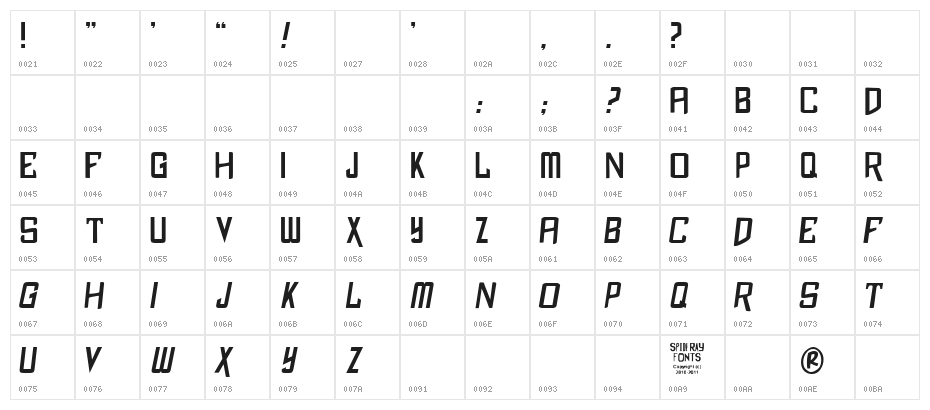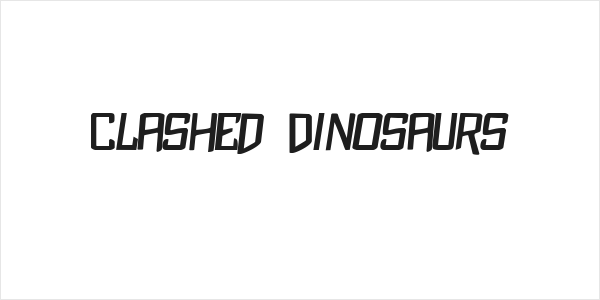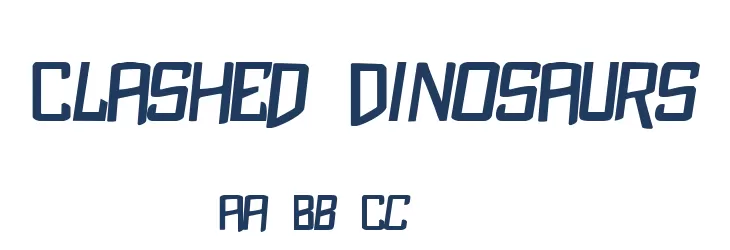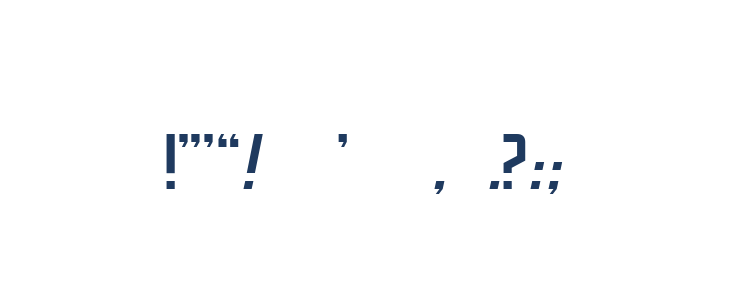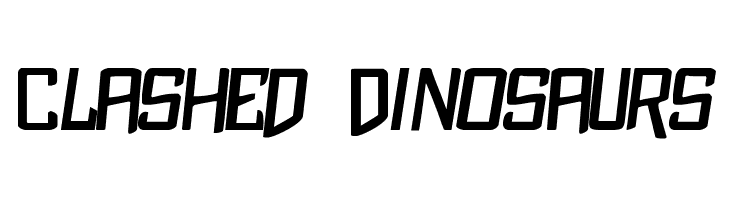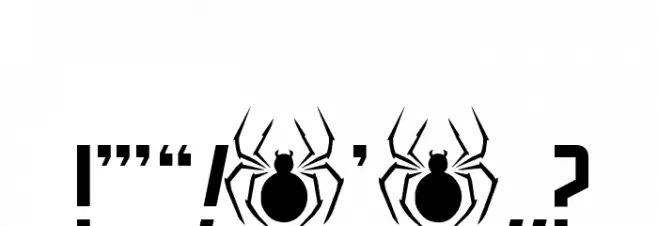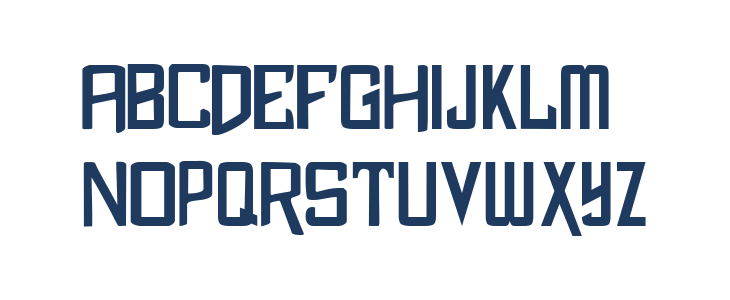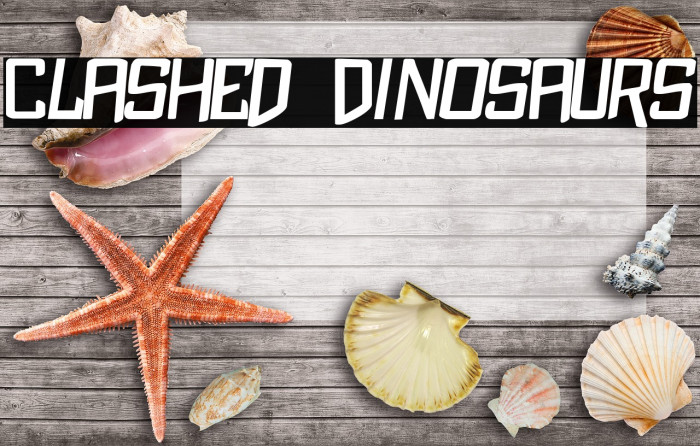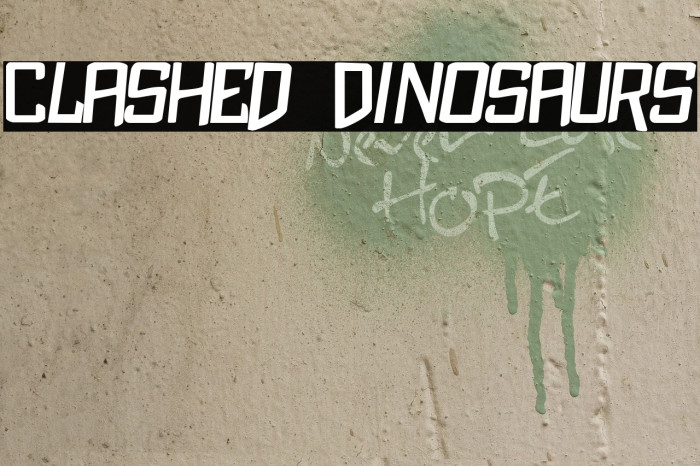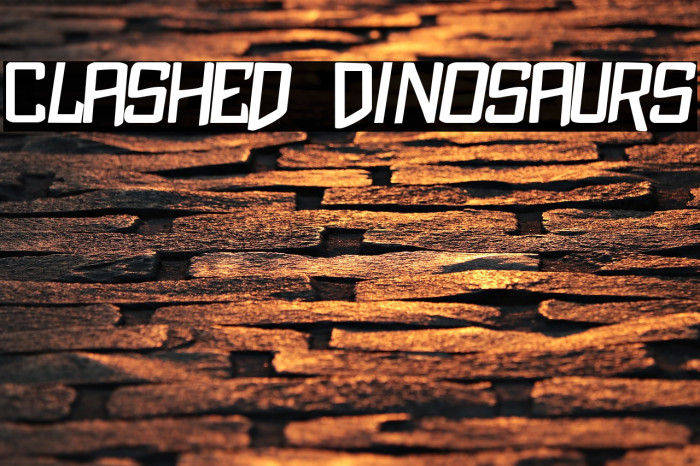
Clashed Dinosaurs Font
Clashed Dinosaurs
| Estilo general | Futuristic, Dynamic |
| Proyectos propuestos | Ideal for sci-fi themed designs, video game titles, posters, and branding that requires a modern and edgy look. |